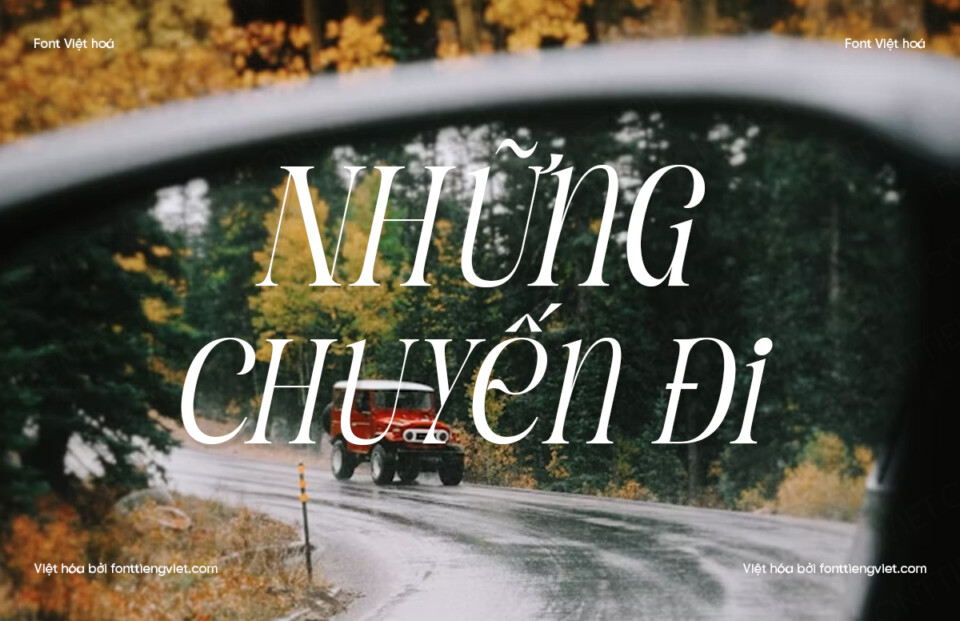
Font Việt hóa 1FTV VIP Argaka Fashion Italic
Giới thiệu về Font Việt hóa 1FTV VIP Argaka Fashion Italic
Trong thế giới thiết kế đồ họa hiện đại, việc lựa chọn một bộ Font Miễn Phí chất lượng luôn là ưu tiên hàng đầu của các nhà sáng tạo. Đặc biệt, Font Việt hóa 1FTV VIP Argaka Fashion Italic nổi lên như một hiện tượng nhờ sự kết hợp hoàn hảo giữa nét thanh lịch cổ điển và hơi thở thời trang đương đại. Đây là phiên bản nghiêng (Italic) nằm trong bộ sưu tập VIP được đội ngũ 1FTV tinh chỉnh kỹ lưỡng, đảm bảo hiển thị mượt mà trên mọi nền tảng số và in ấn. Với đường nét sắc sảo, bộ font này không chỉ đơn thuần là công cụ đánh máy mà còn là linh hồn cho các tác phẩm nghệ thuật cần sự sang trọng và phá cách.
Đặc điểm nổi bật của Font Việt hóa 1FTV VIP Argaka Fashion Italic
Thiết kế mang phong cách Editorial thời thượng
Font Việt hóa 1FTV VIP Argaka Fashion Italic sở hữu những nét chữ mảnh mai nhưng dứt khoát, mô phỏng phong cách chữ trên các tạp chí thời trang danh tiếng như Vogue hay Harper’s Bazaar. Độ nghiêng của font được tính toán chính xác để tạo cảm giác chuyển động linh hoạt, giúp bố cục thiết kế trở nên thoát xác và không còn khô cứng. Các chi tiết như chân chữ (serif) và điểm nối được bo tròn tinh tế, tạo nên sự hài hòa tuyệt đối cho các đoạn văn bản ngắn hoặc tiêu đề chính.
Khả năng tương thích và hỗ trợ tiếng Việt hoàn hảo
Một trong những rào cản lớn nhất khi sử dụng font ngoại nhập là lỗi dấu tiếng Việt. Tuy nhiên, với phiên bản Font Việt hóa 1FTV VIP Argaka Fashion Italic, người dùng hoàn toàn có thể yên tâm. Các dấu thanh như huyền, sắc, hỏi, ngã, nặng được thiết kế lại để không bị chồng chéo hay quá thô so với thân chữ chính. Điều này giúp các bạn học sinh, sinh viên hoặc giáo viên dễ dàng ứng dụng vào các bài thuyết trình, báo cáo hay thiết kế bìa sách mà vẫn giữ được tính thẩm mỹ cao nhất.
Ứng dụng thực tế của Font Việt hóa 1FTV VIP Argaka Fashion Italic
Sáng tạo logo và nhận diện thương hiệu
Nhờ vẻ ngoài quý phái, Font Việt hóa 1FTV VIP Argaka Fashion Italic cực kỳ phù hợp cho các dự án thiết kế logo cho ngành làm đẹp, spa, hoặc nhãn hàng quần áo cao cấp. Khi kết hợp với các gam màu trung tính như vàng đồng, đen hoặc trắng, font chữ này sẽ giúp thương hiệu của bạn tỏa sáng và ghi dấu ấn mạnh mẽ trong lòng khách hàng ngay từ cái nhìn đầu tiên.
Thiết kế poster và ấn phẩm truyền thông
Đối với các bạn trẻ yêu thích làm nội dung trên mạng xã hội, sử dụng font chữ này cho các tiêu đề poster hay banner sẽ tạo nên sự khác biệt rõ rệt. Nó giúp thông điệp truyền tải trở nên có chiều sâu và nghệ thuật hơn. Bạn có thể sử dụng font này cho các trích dẫn (quotes) truyền cảm hứng hoặc làm tiêu đề cho các video lookbook thời trang.
Kết luận về bộ font đẳng cấp